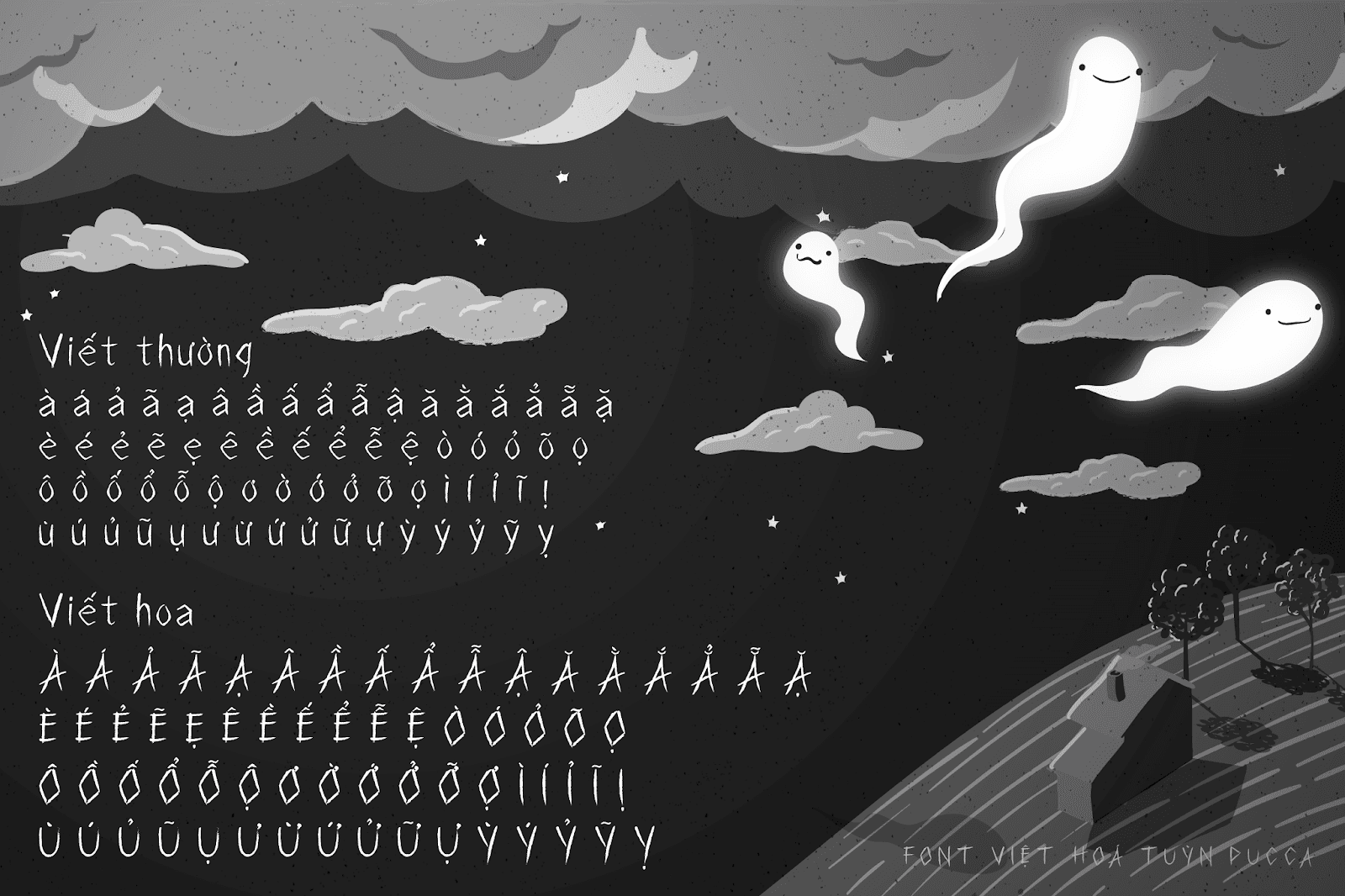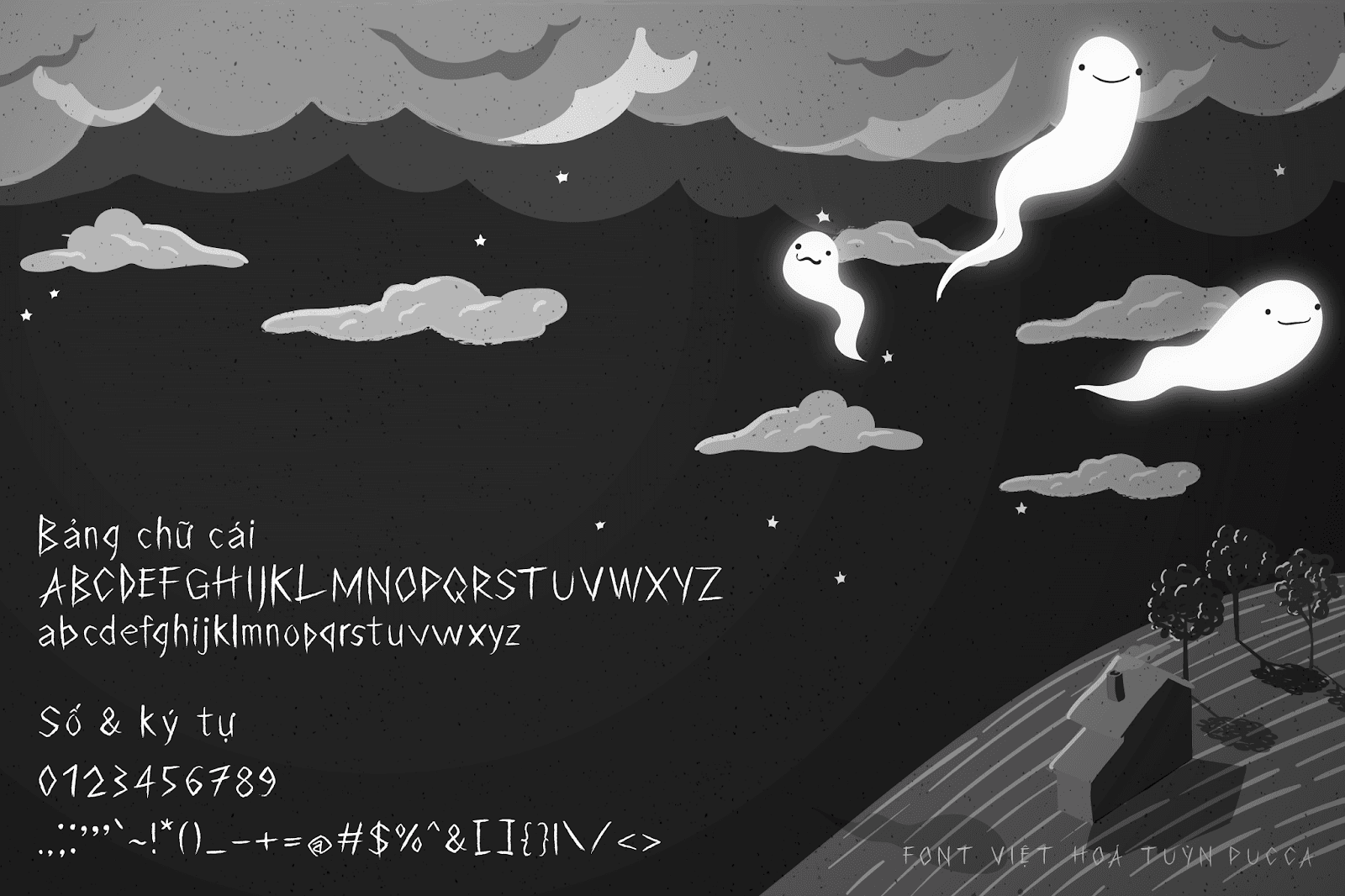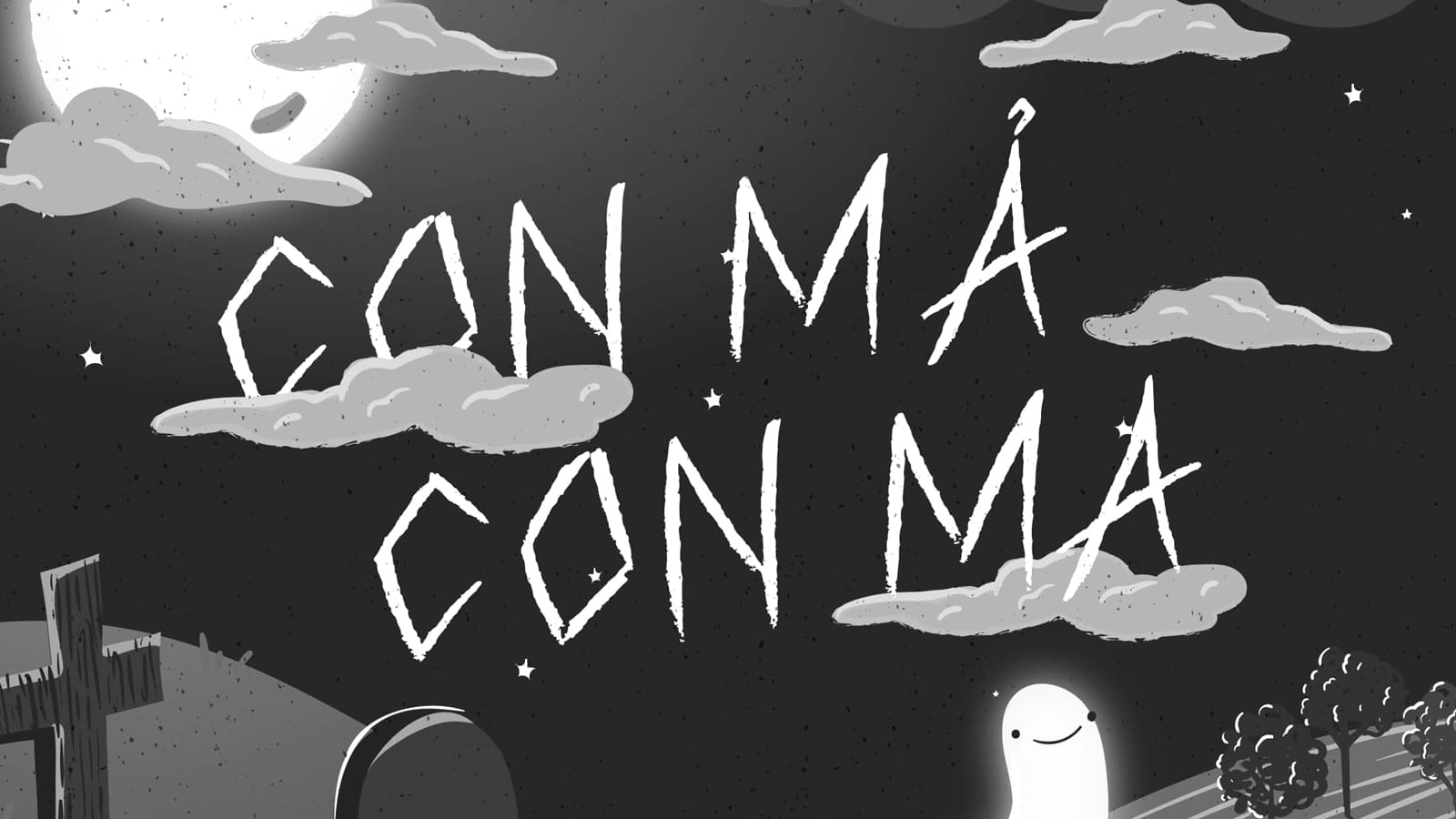
Lost Land Font Việt Hóa đây là một font chữ vẽ tay theo phong cách kinh dị, font chữ này phù hợp cho các thiết kế trang bìa, logo, tiêu đề, tiêu đề tạp chí. Font chữ hỗ trợ đa ngôn ngữ, được Việt hóa đầy đủ bởi Tuỳn Pucca, đã được chỉnh sửa và tối ưu hoàn chỉnh nhất.